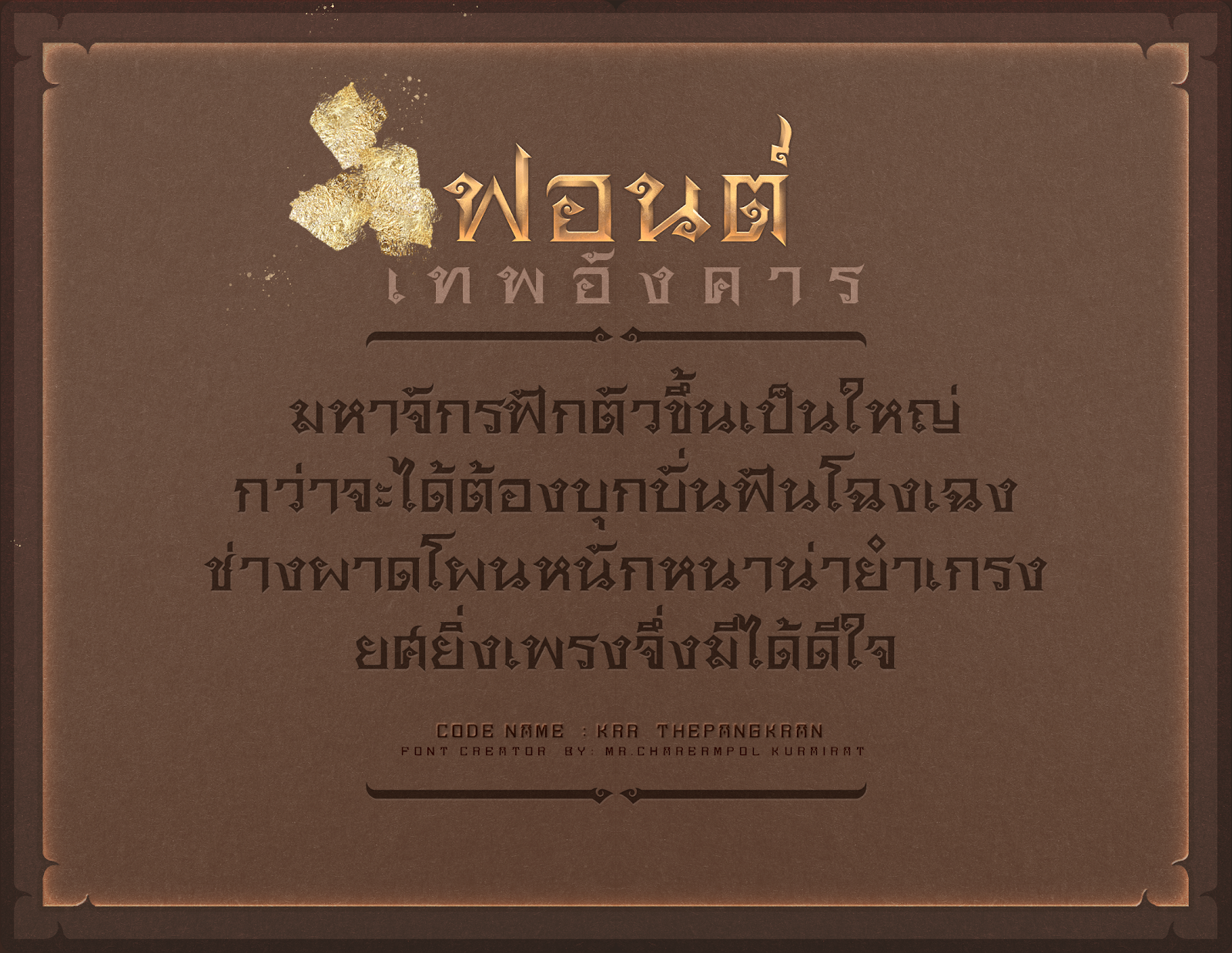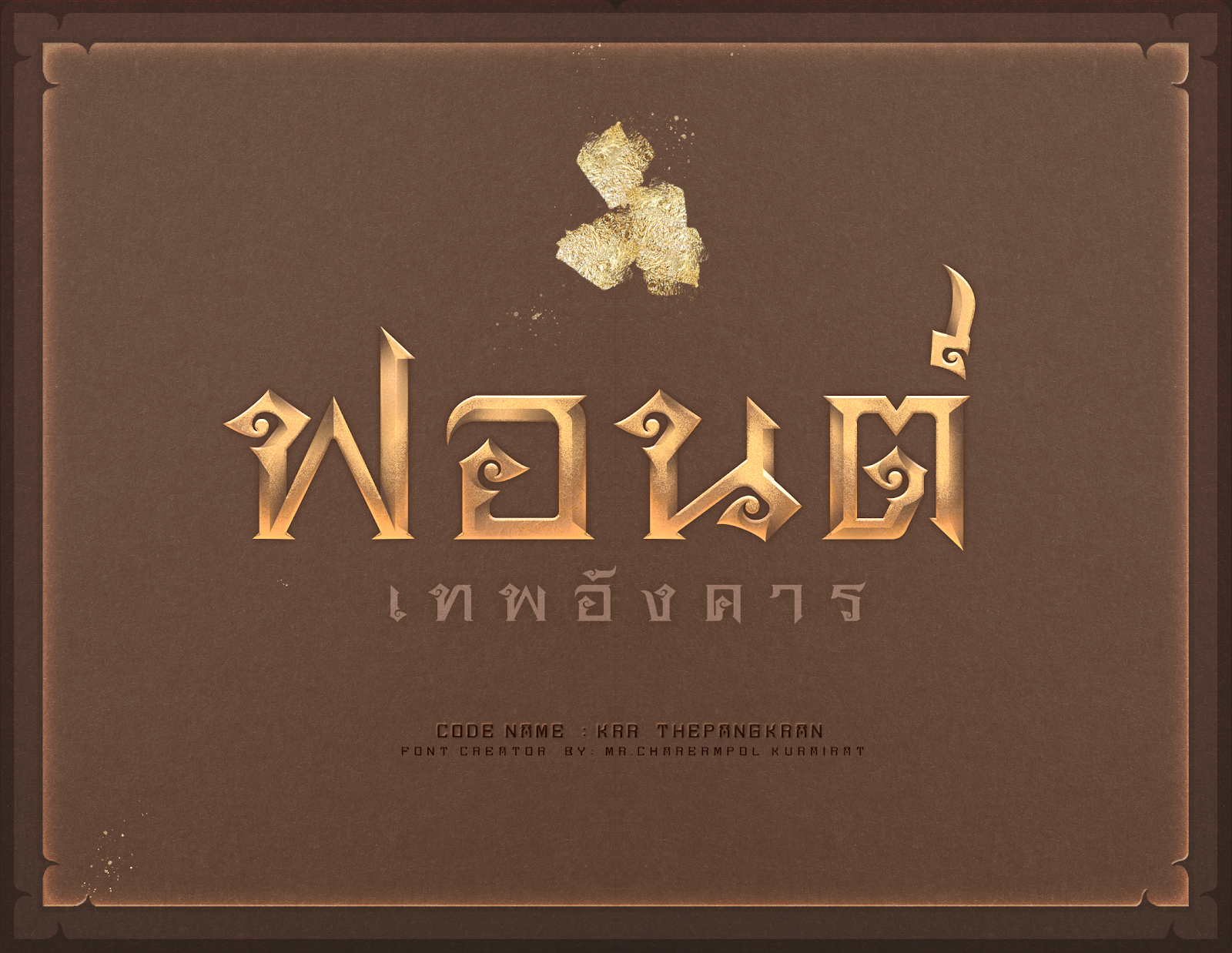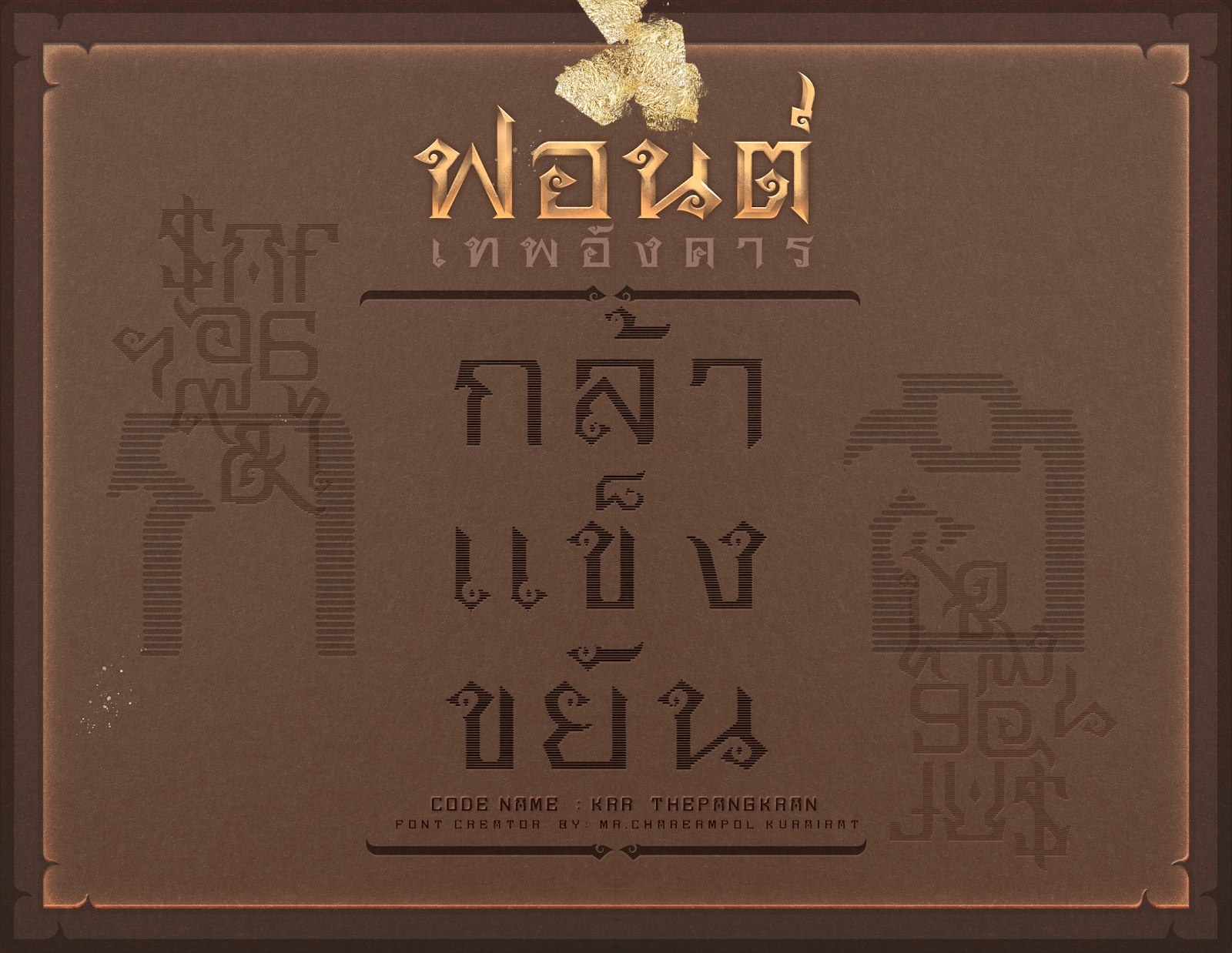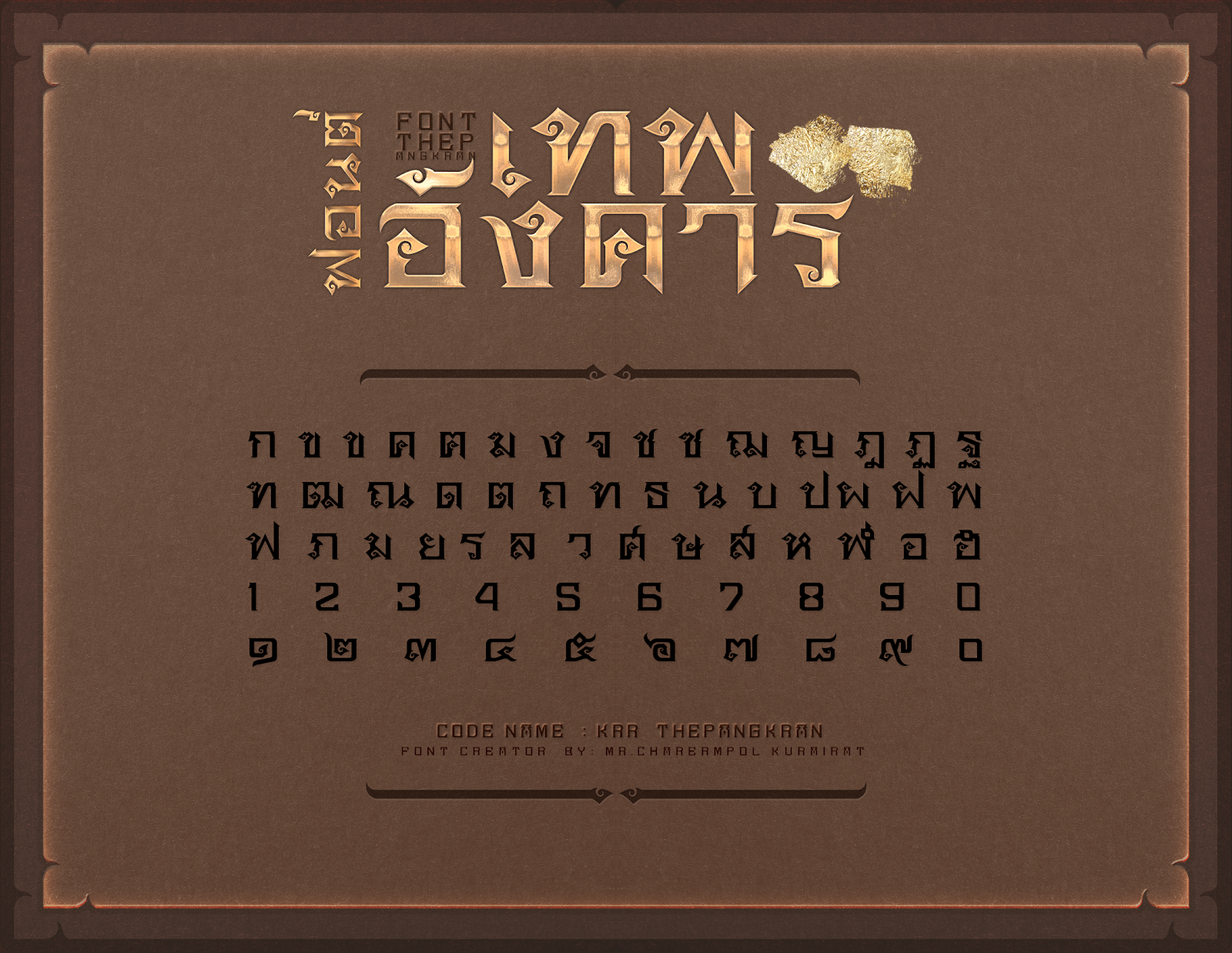
เค อาร์ อาร์ เทพอังคาร (KRR THEPANGKRAN)
สวัสดีวันดีๆ พร้อมปล่อยฟอนต์ตัวที่ 3  ของชุด ฟอนต์นพเคราะห์ครับ "เค อาร์ อาร์ เทพอังคาร (KRR THEPANGKRAN)"
ฟอนต์แนวไทยๆ ผมมีความตั้งใจอยากทำฟอนต์ชุด นพเคราะห์ (ดาวทั้ง 9)
อาทิตย์ -จันทร์- อังคาร – พุธ- เสาร์ -พฤหัสบดี -ราหู -ศุกร์- เกตุ
ฟอนต์ เทพอังคาร มีสองภาษา ไทย- อังกฤษ
สอง รูปแบบ ตัวปกติ-ตัวขีด ใช้ได้ MAC / PC
ออกแบบโดย : Mr.Charermpol Kurairat